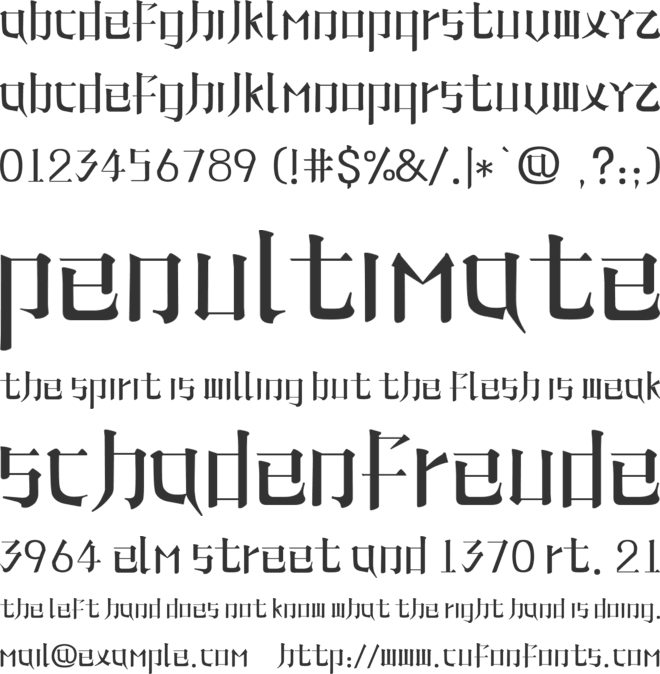
Line phone font
在字母的设计中,我希望每一笔,都尽可能的接近中文笔划的特点。而不是简单的将中文笔划进行变形,旋转,或者镜像等等。从b,p,d,q这几个字母的设计中能体现出我们的一些想法。 "Line Phone Font"的设计原则是: 1、每个字母都是单独的完整的图形,从视觉上应该是统一的而不是分离的。   More... 2、尽量追求每个笔划都来自合理的中文解构。 3、反复测试之母之间的间距组合。
Translation form google Line phone font "is a font of English, also known as" Song, the Stroke "(Song intended to stroke the body). Is taken from the charm of the Chinese "Arial", sample of the composition characteristics of the Chinese, resulting in a unique visual effects.
In the design of letters, I hope each, are as close as possible to the characteristics of Chinese strokes. Rather than a simple Chinese strokes deformation, rotation, or mirror, and so on. B, p, d, q and a few letters of the design to reflect some of our ideas. "Line Phone Font" design principle is: 1, each letter is separate graphics from the vision should be uniform rather than separation. 2, as the pursuit of each stroke from the Chinese deconstruction. 3, repeated combination of the spacing between the test the mother.